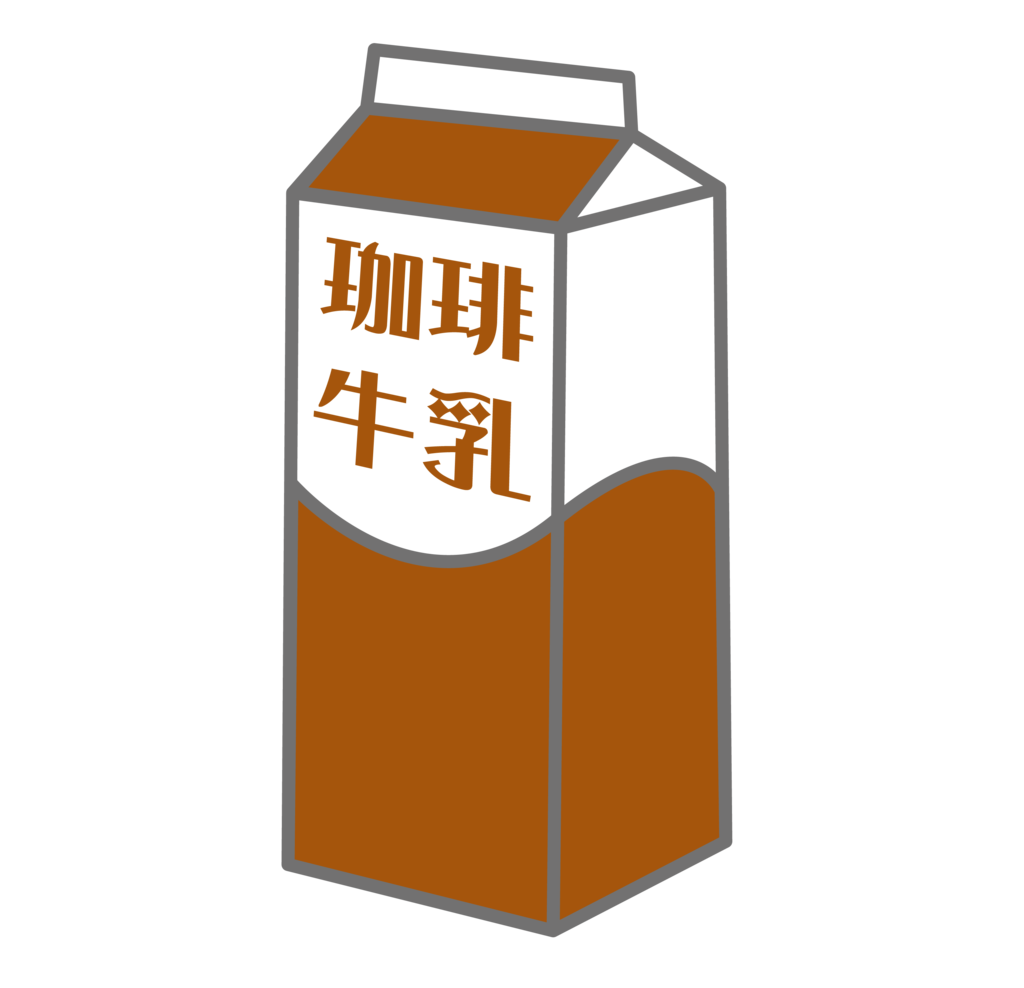
ロマン雪
図案化せる実用文字から着想を得て、図中の婦人の華麗な装いや愛らしいスタイルをヒントに古典ロマンの雰囲気を再現した書体。
ロマン雪の組見本(ロマン雪A)
新元号「令和」ロマン雪書体見本
新元号「令和」のロマン雪の書体見本。
ロマン雪採用事例「大逆転裁判1&2 -成歩堂龍ノ介の冒險と覺悟」
カプコンが開発・販売する「大逆転裁判」シリーズにダイナフォント「ロマン雪」が採用されている。
一部、フォントを加工しての使用のようだ。
タイトル部分の文字だけでなく、ゲームのUIでもロマン雪の使用が確認できる。
ロマン雪採用事例「たまごの魔法屋トワ」シリーズ
文響社が発売する、宮下 恵茉氏著作で、星谷 ゆき氏がイラスト、稲永 明日香氏がデザインを担当した児童文学「たまごの魔法屋トワ」シリーズに、ダイナフォント「ロマン雪」を含むロマン風書体が採用されている。
採用理由は物語の舞台となる魔法世界の雰囲気にぴったりだったためとのこと。
ロマン雪以外に、ロマン輝と優雅宋も採用されている。
ロマン雪採用事例「洋菓子店アルセーヌ」シリーズ
九条菜月氏著書で、装画をイラストレーターのMinoru氏、装幀をデザイナーの西村弘美氏が担当した、中央公論新社の中公文庫刊行による書籍シリーズ「洋菓子店アルセーヌ」のタイトルに、ダイナフォント「ロマン雪」が採用されている。
採用理由は、洋菓子店の看板のようなタイトルにしたかったため、装飾のある少し懐かしい感じたため、また、フォントの雰囲気がケーキの華やかなイラストに合うと思ったため。
ロマン雪採用事例の紹介
立東舎の手塚治虫発行作品のタイトルで使用。立東舎の定本 薔薇の記憶のタイトルにも使用されている。また河出文庫の戦力外捜査官やポプラ文庫の真夜中のパン屋さんシリーズのタイトルで使用されている。